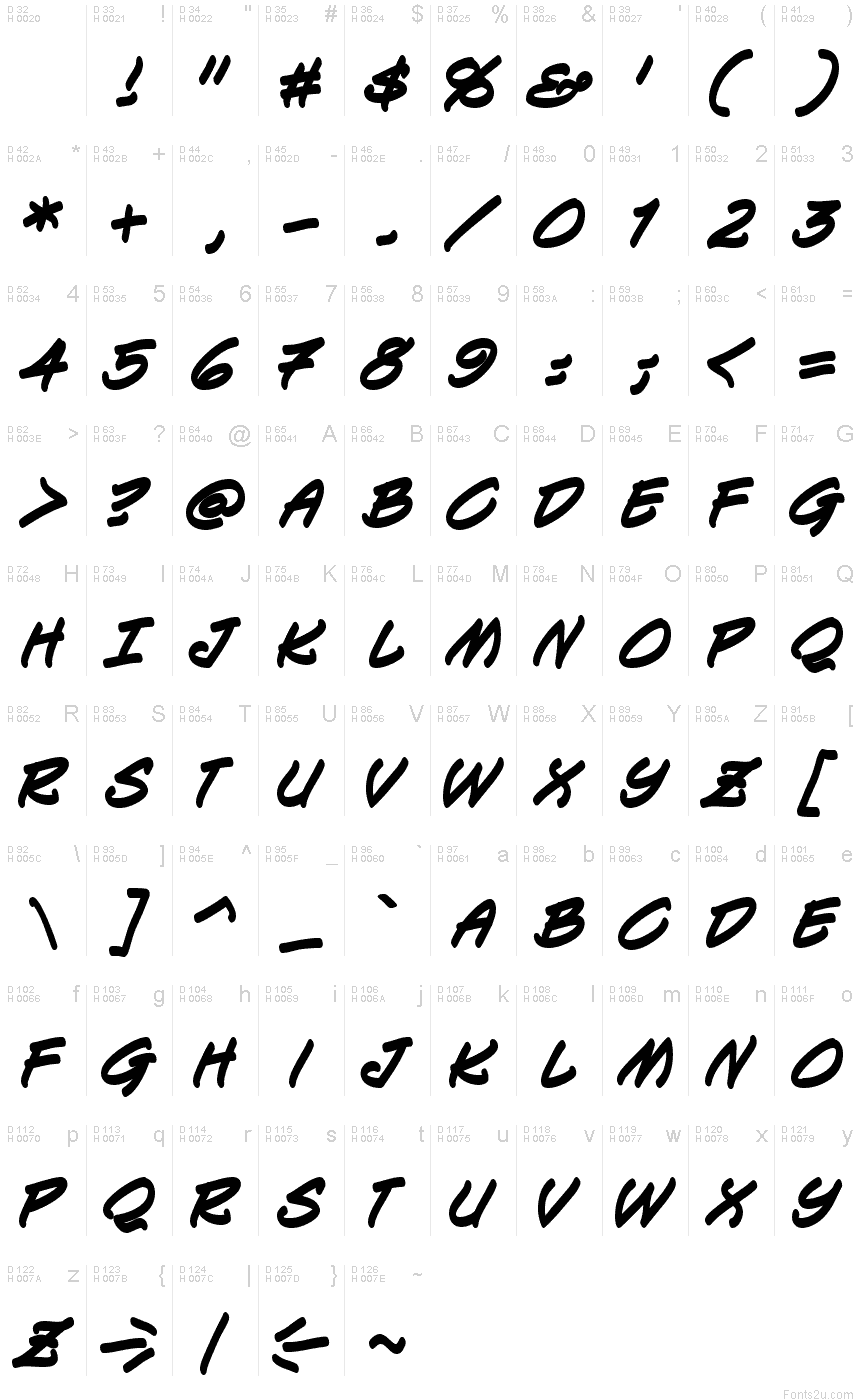
Keelhauled BB Bold 字体
Keelhauled BB Bold
由 Nate Piekos 设计的 Keelhauled BB Bold 是一款免费手写字体,充满张扬的冒险气息。其厚重的墨迹笔触、锐利的角度和前倾的字势,仿佛是用粗马克笔一气呵成挥就的,赋予标题十足的漫画冲击力和一丝海盗般的狂野感。字母间距紧凑,营造出一种呼之欲出的、高密度的视觉张力。
这款免费字体非常适合漫画排版、海盗或航海主题海报、游戏标题、万圣节海报、YouTube 封面以及各种个性化周边设计。将 Keelhauled BB Bold 用于大字号标题时,其类似毛笔的曲线和厚重的韵律感尤为突出。建议搭配一款简洁的窄体无衬线字体作为正文,在保持阅读性的同时,让 Keelhauled BB 尽情展示其个性。